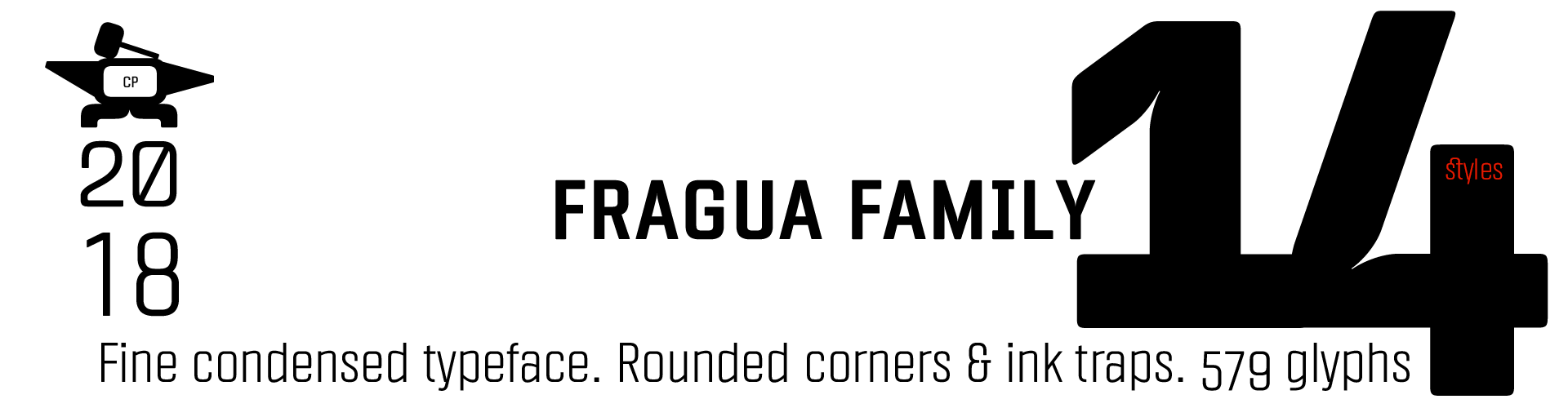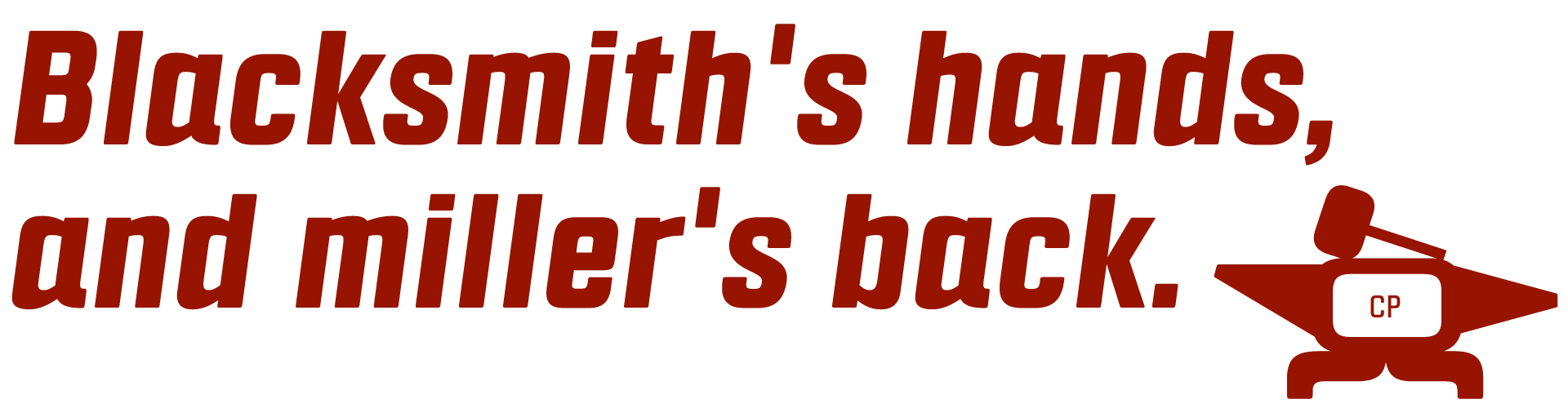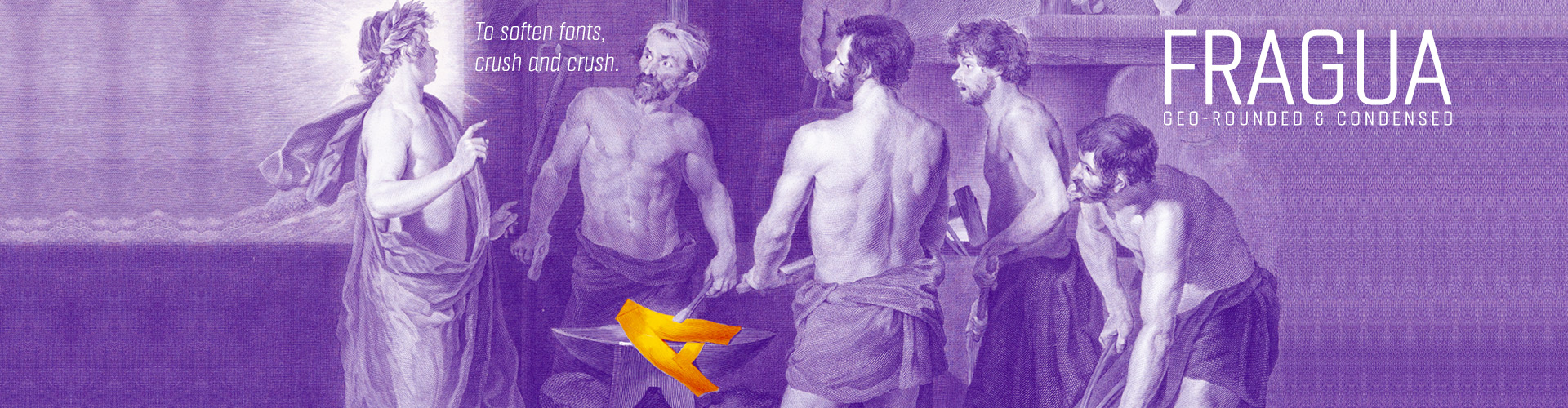
Geo-Rounded & Condensed
Estilo: Sans Serif, Geometric, Condensed, Italics, Rounded
Proporción: Extra Light, Light, Regular, Medium, Semi Bold, Bold & Extra Bold + Italics
Glyphs: 579
Alternates: 34
Autor: deFharo
Año de publicación: 2018.
Está tipografía está especialmente diseñada para la composición publicitaria y editorial, comportándose correctamente tanto en textos cortos y medios como en titulares donde se necesite ahorro de espacio horizontal, siendo un sistema tipográfico ideal para señalización, diseño editorial o corporativo.
La tipografía dispone de 579 glifos (Latin Extended-A) con funciones avanzadas OpenType, varios juegos de números, minúsculas alternativas y el símbolo del Bitcoin, con soporte para cualquier idioma europeo o centro europeo. Fragua Sans Condensed también incluye funciones OpenType (Compatibles con InDesign, QuarkXpress, Photoshop e Illustrator.